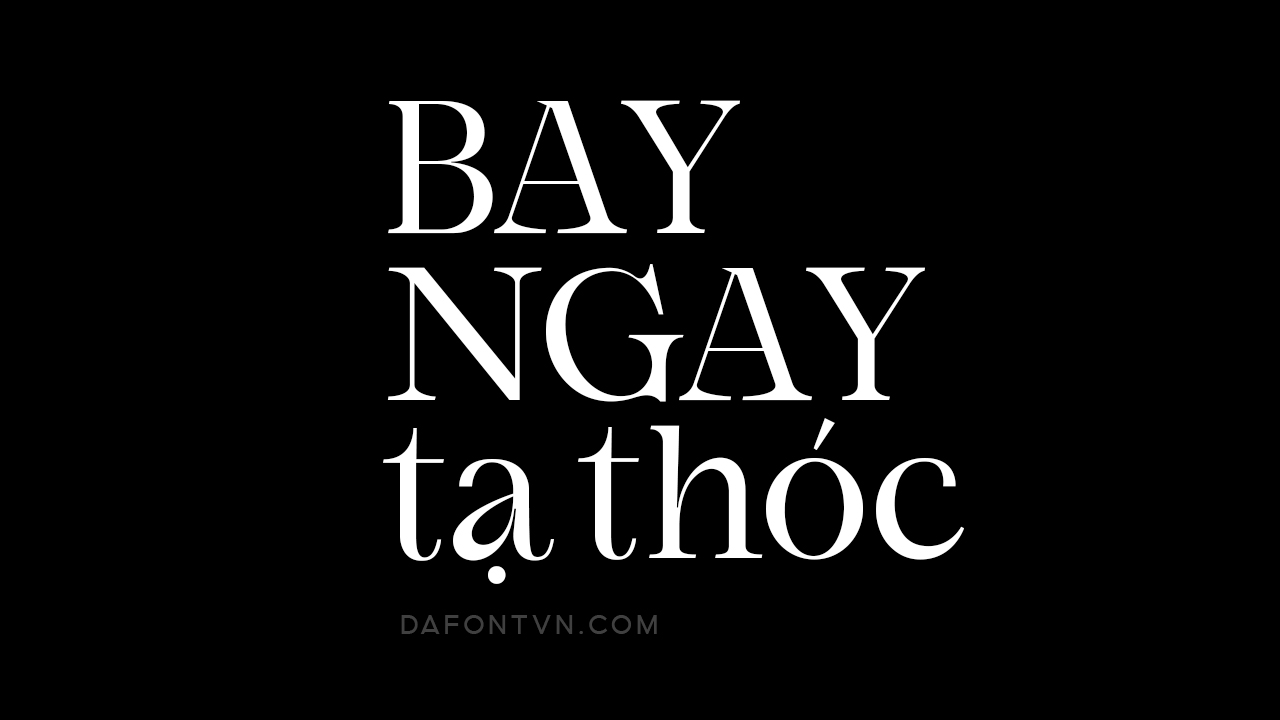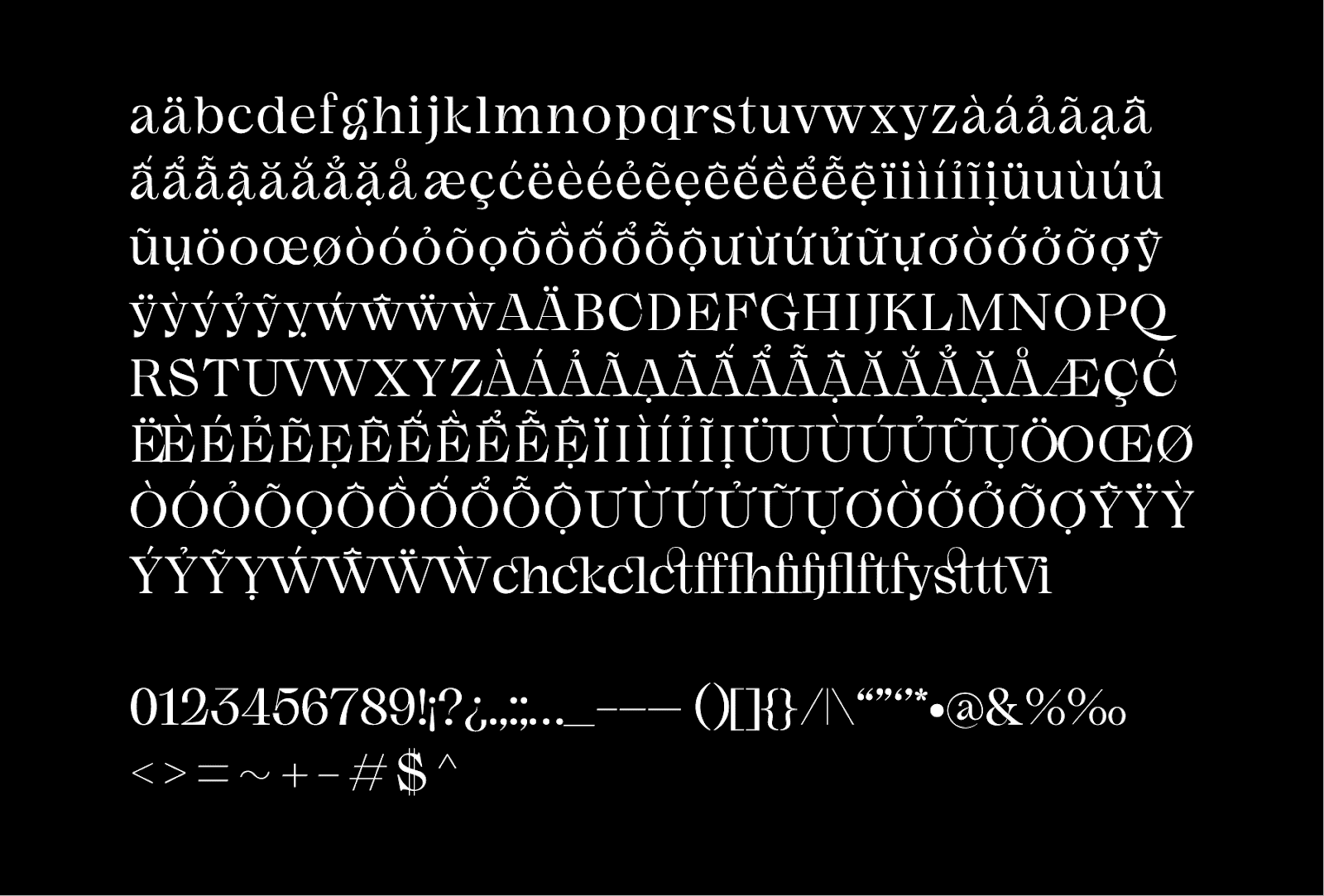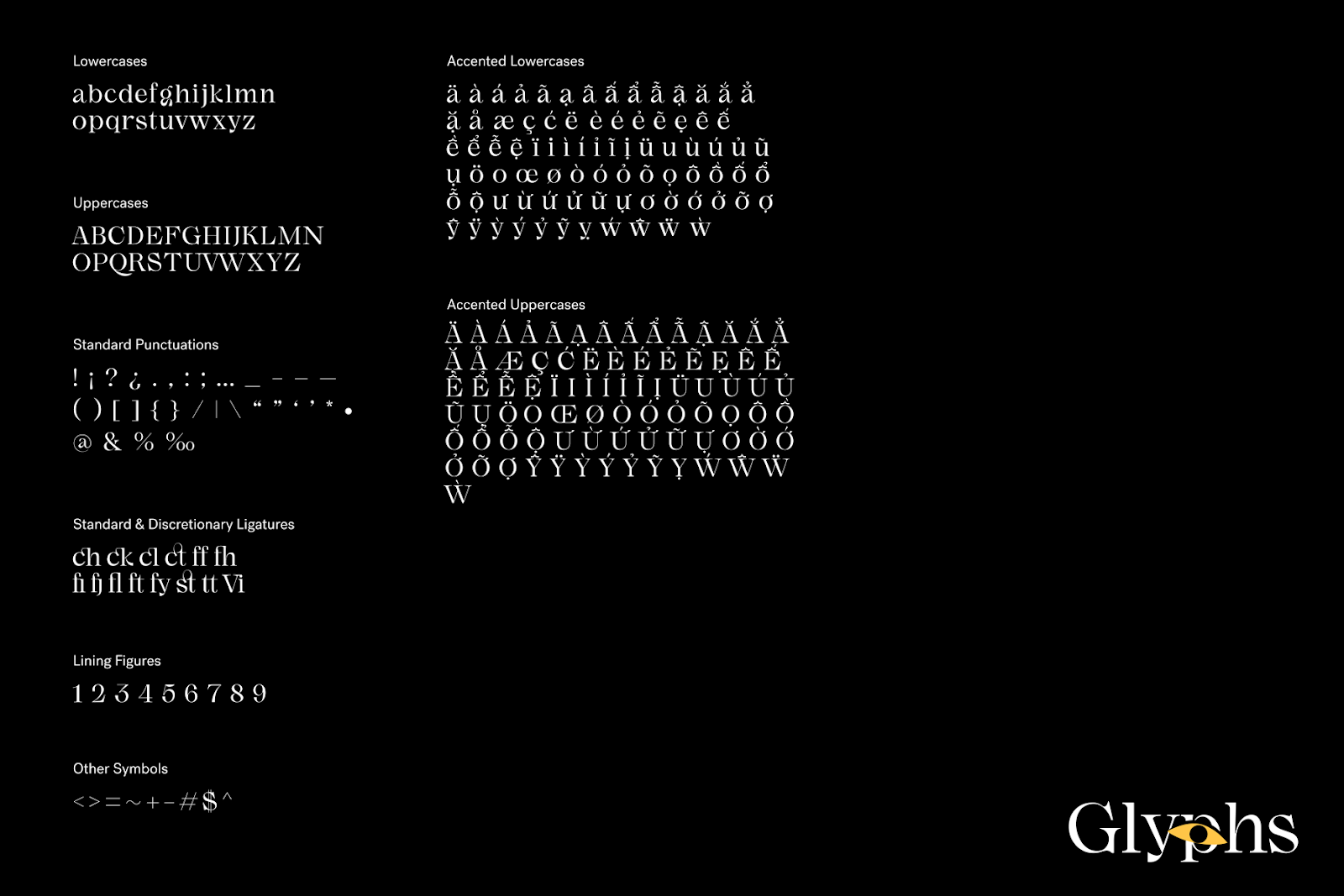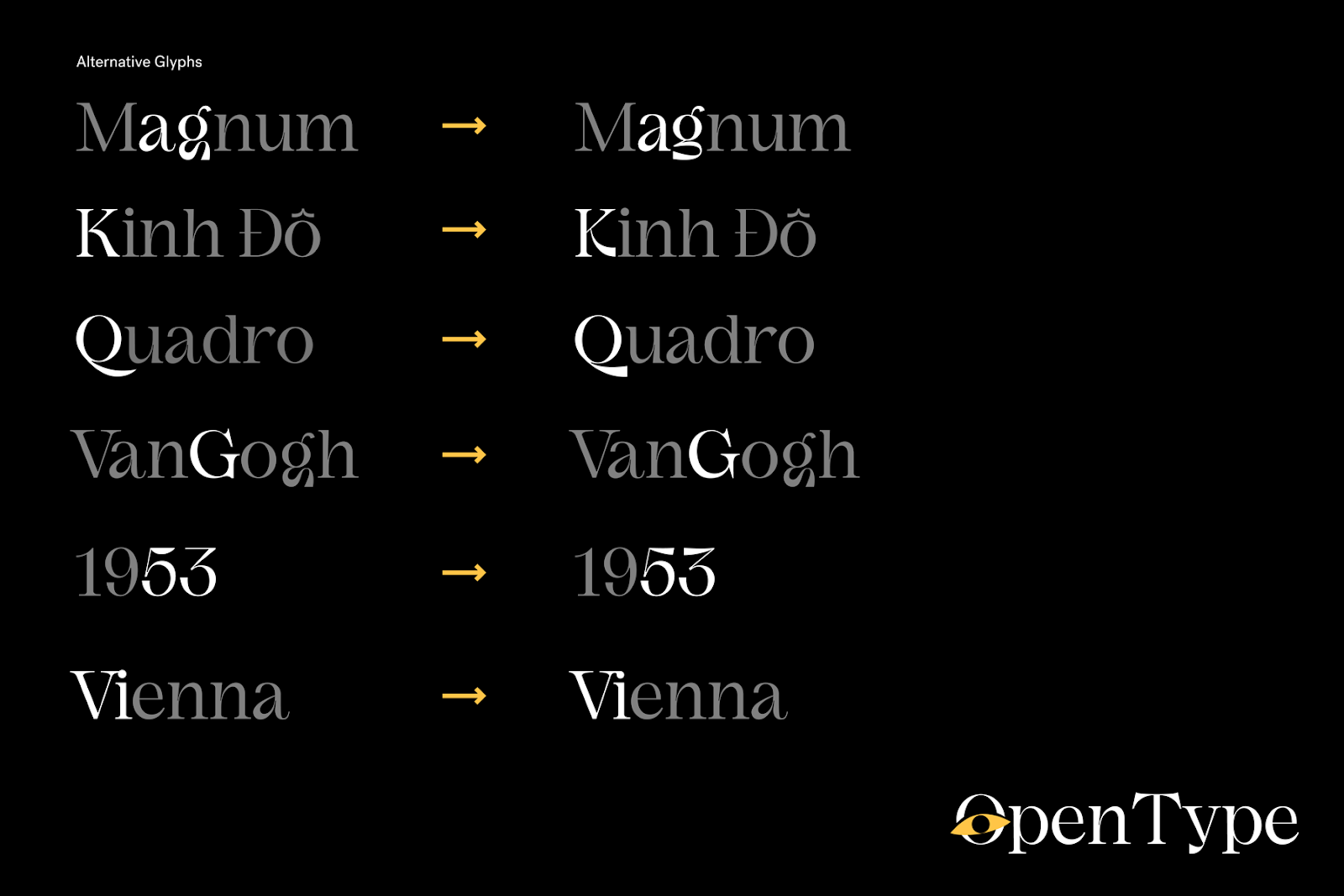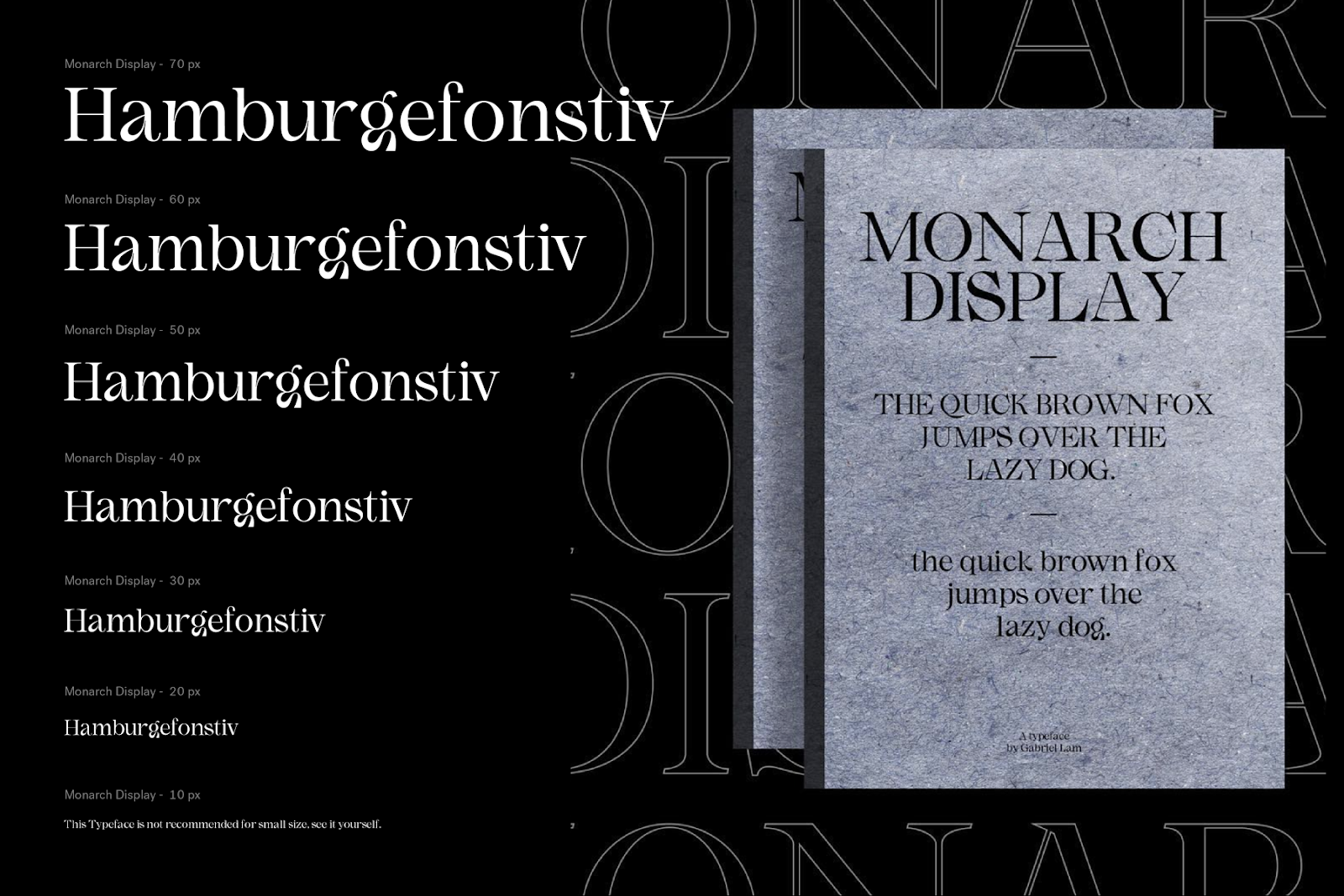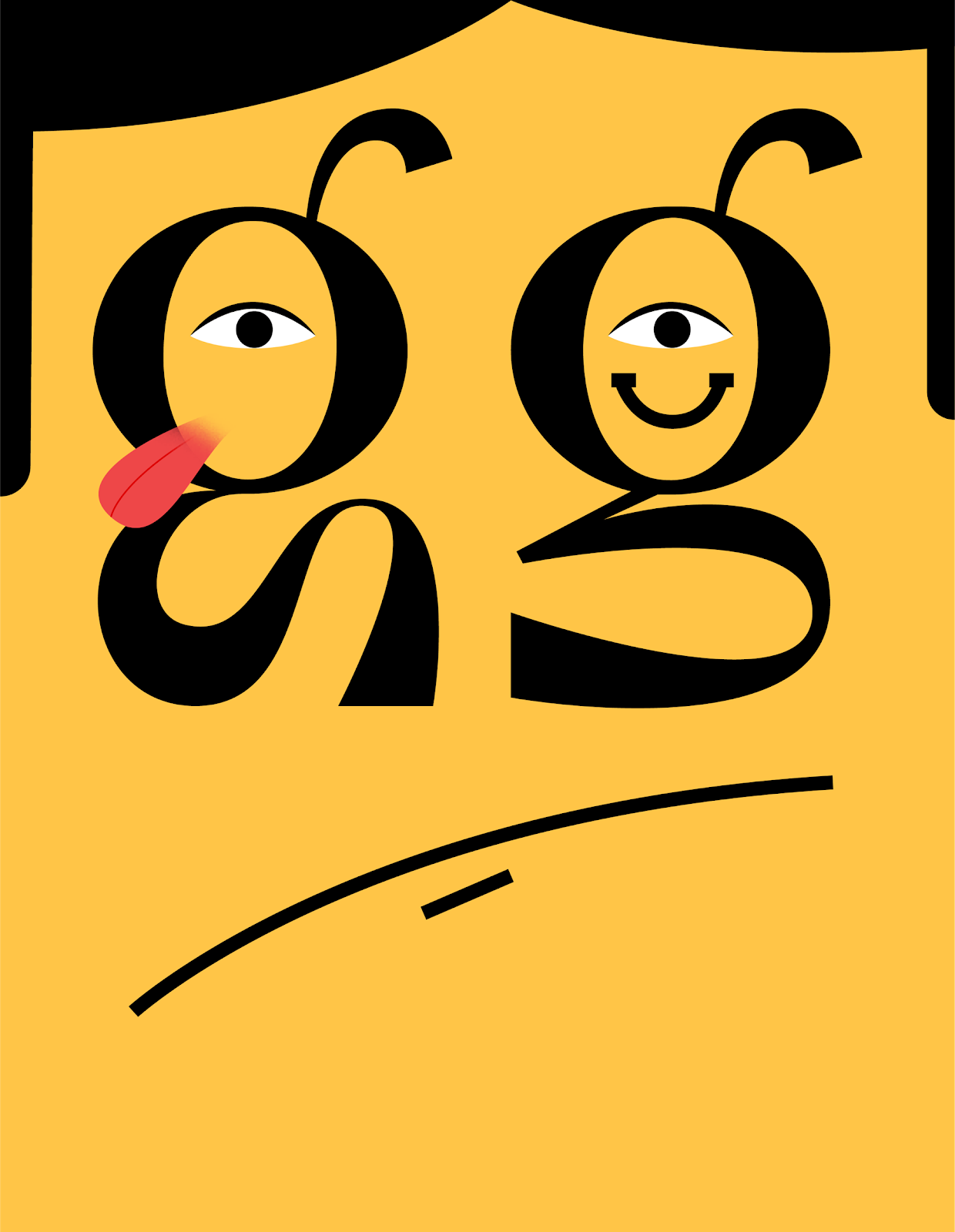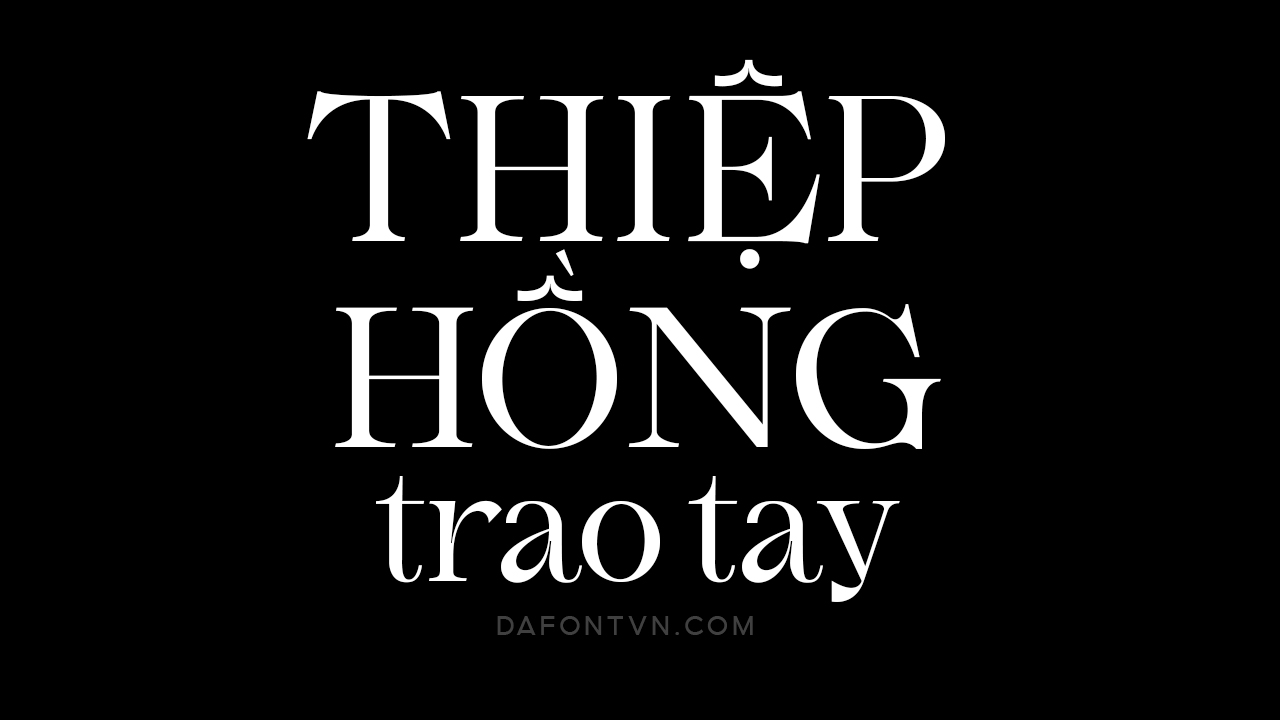
Font Monarch Display là font được thiết kế bởi Gabriel Lam – 1 kiểu font tiếng Việt với các nét được thiết kế cực đẹp hiển thị tốt ở nhiều kích thước khác nhau. Font phù hợp cho nhiều thiết kế khác nhau như thiệp mời, sản phẩm, bìa sách…